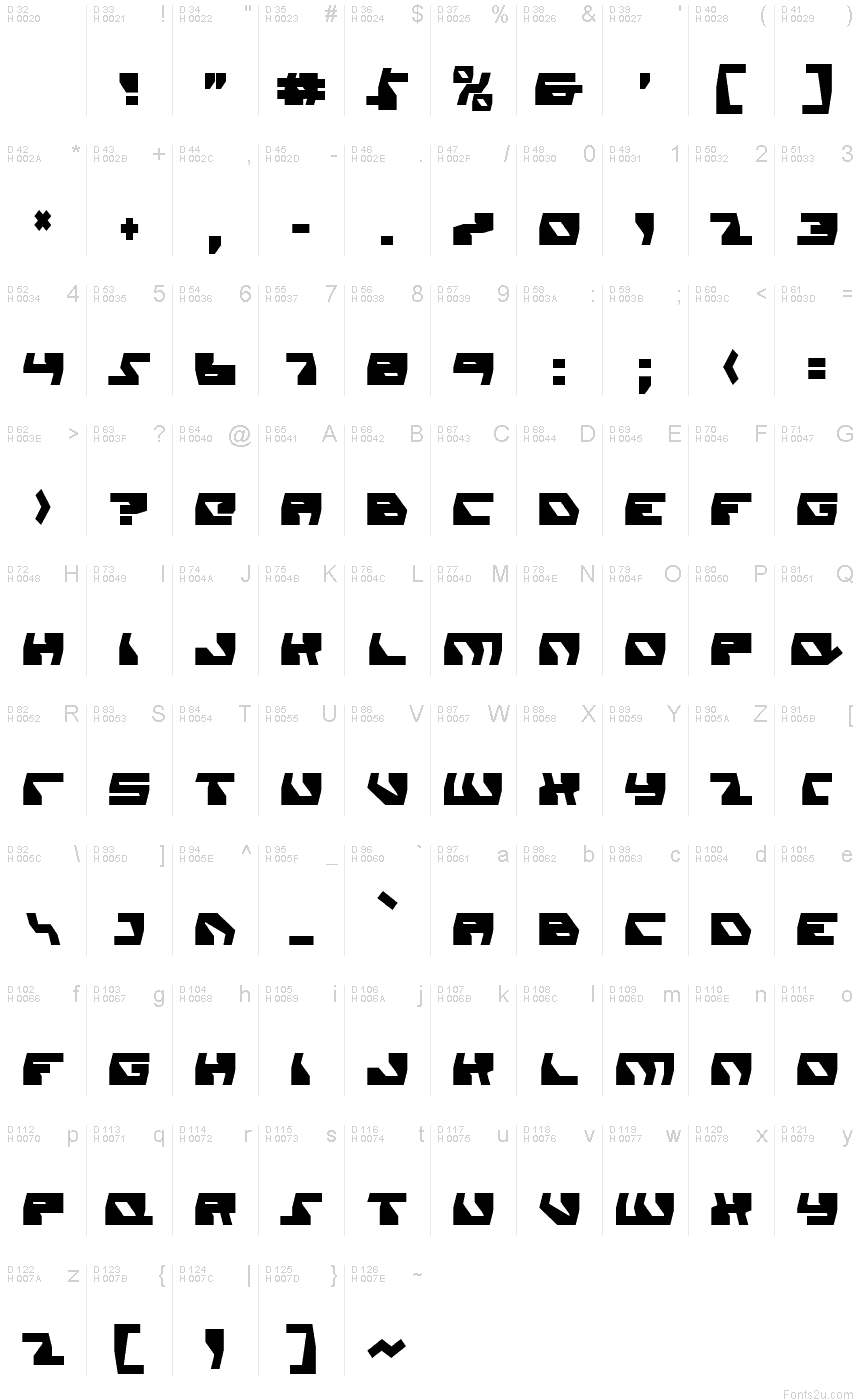
Daedalus Condensed od Iconian Fonts to darmowy font w stylu techno stencil z mocnym charakterem science-fiction. Litery zbudowane są z ostrych, przyciętych płaszczyzn i podzielonych geometrycznych form, co nadaje krojowi mechaniczny rytm – bardziej przypominający oznaczenia statków kosmicznych czy futurystyczny branding z epoki gier arcade niż neutralne liternictwo ekranowe.
Krój idealnie pasuje do logo gier, plakatów, okładek albumów, plansz tytułowych oraz krótkich projektów brandingowych, gdzie potrzebny jest ten industrialny, "wycinany" efekt. Używaj go w kompaktowych nagłówkach, insygniach i nazwach frakcji; powtarzające się wcięcia i załamane krawędzie nadają nawet krótkim liniom techniczny, inżynieryjny charakter.
Daedalus Condensed
Dan Zadorozny